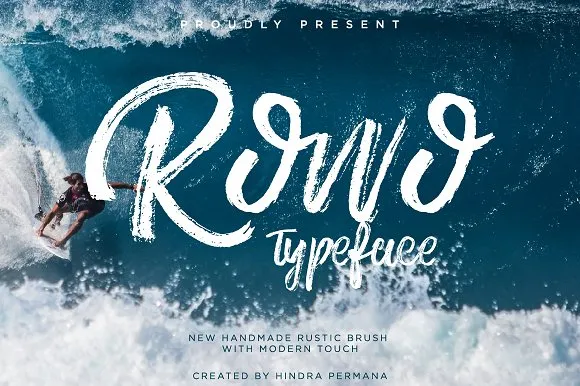
Rowo Brush Font – Download Grátis
Introduzimos a Rowo Brush Font! Esta fonte premium foi criada por ndro e está disponível gratuitamente hoje para download na CreativeMarket. A Rowo traz uma sensação naturalista ao mesmo tempo moderna, revigorando o look de letra customizada à mão com um toque de arte. Ideal para designers de envelopes, criação de logotipos, formatação de títulos, invitações de casamento, etiquetas, newsletters, sinalização, panfletagem, selos e até mesmo em estandartes. A Rowo Typeface é versátil e pode ser usada para uma variedade de projetos, sempre garantindo um resultado impecável. Adquira-a hoje e dê vida à sua próxima arte digital com o toque especial da Handwritten!